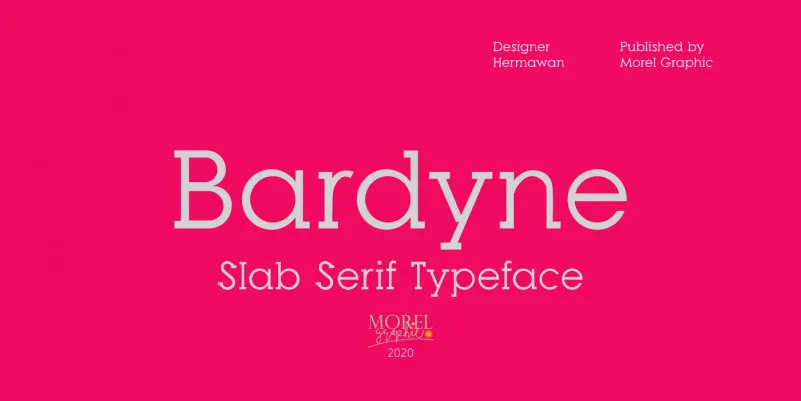
Estamos muito felizes por oferecer a você uma breve descrição envolvente da fonte Bardyne Slab Serif. Esta é uma tipografia slab serif criativa e vibrante com um forte caráter pessoal, repleta de elementos que facilitam a leitura. Inclui letras maiúsculas, minúsculas, números, pontuação e símbolos, inclusive caracteres não-latinos. Bardyne Slab Serif é uma tipografia slab serif concebida para apresentar um estilo limpo, legível, apto para múltiplas finalidades — desde texto até gráficos de produto, logo, identidade corporativa ou infográfico. Esta fonte foi projetada com a intenção de ser fácil de ler tanto na tela quanto em impressão. É perfeitamente adequada para um vasto leque de aplicações e mídias, como textos legíveis, displays visuais, headlines, identidades corporativas, logos, produtos ou infográficos, além de outras utilizações. Não hesite em explorar a versatilidade desta fonte em sua próxima criação visual.